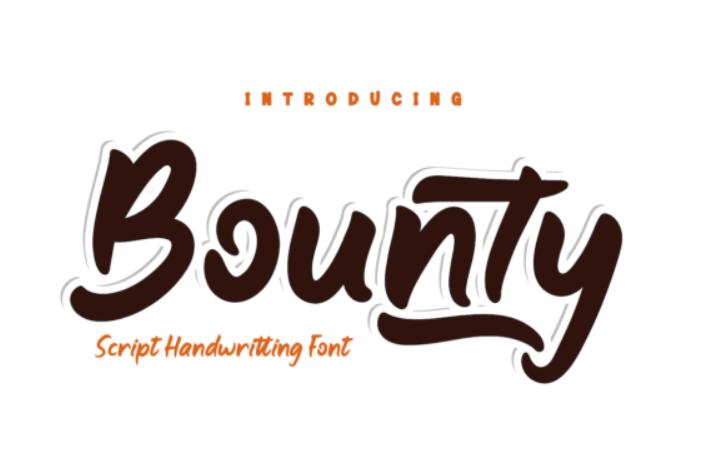
Bounty - это веселый и модный матовый рукописный шрифт. Он имеет современный, но причудливый стиль и, несомненно, погрузит ваши проекты в волшебный мир.